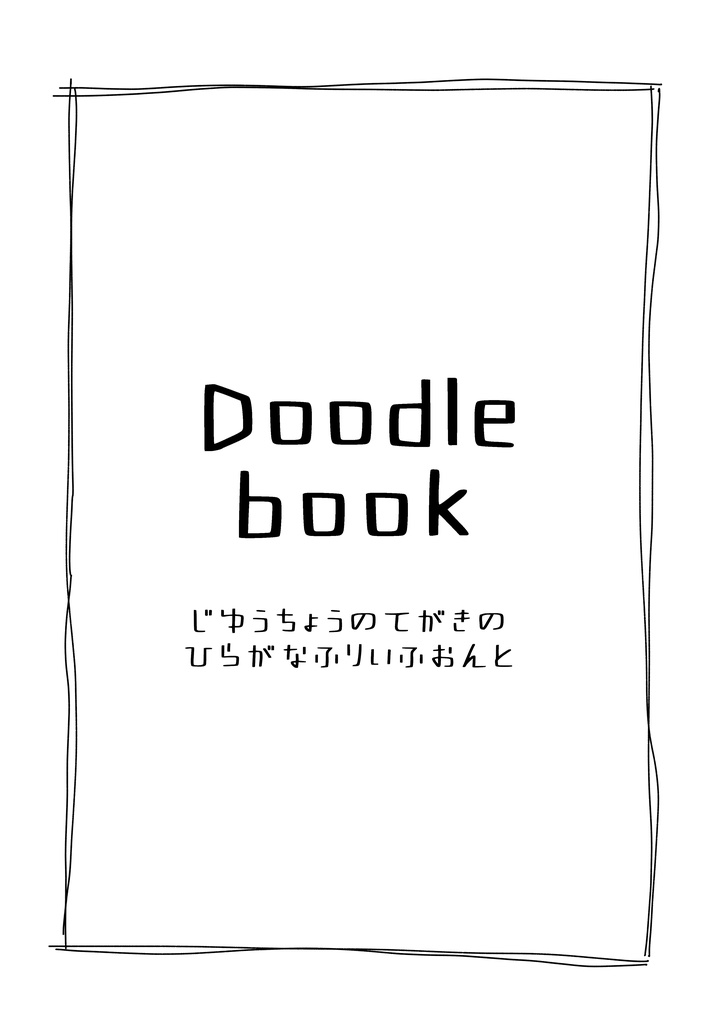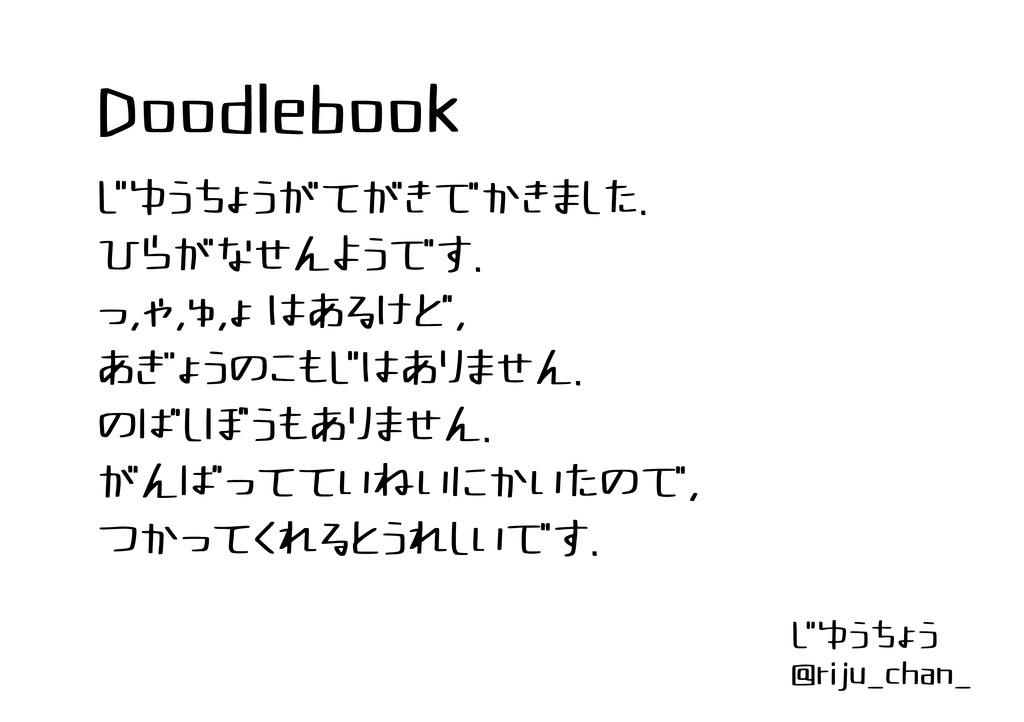
【フリーフォント】Doodlebook
利き手が腱鞘炎になって絵が描けなくなったので、暇つぶしに手書き文字をフォントにしました。 フリーフォントです。 自分用に作ったので、クオリティは高くないです。 頑張って丁寧に書いたので、使ってくれると嬉しいです。 ☆アルファベット、数字、記号もあるよ!( https://pluie173.booth.pm/items/5053396 ) 〇対応文字 ひらがなのみ ・小さい文字は「っ」「ゃ」「ゅ」「ょ」のみです。 ・濁音、半濁音も対応してます。 〇使用可能 ・個人、商用問わず使用可能です。 ・使用報告、クレジット等は不要ですが、していただけるととても嬉しい気持ちです。 〇禁止用途 ・データそのものの二次販売/二次配布 ・変形/加工等をしての二次販売/二次配布 ・自作発言はご遠慮ください。 ・著作権の放棄はしておりません。 使用報告や不備などはX(旧Twitter)(@riju_chan_)、もしくはマシュマロ( https://marshmallow-qa.com/riju_chan_ )へお願いします。